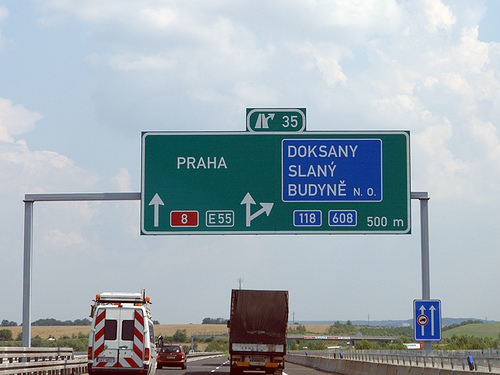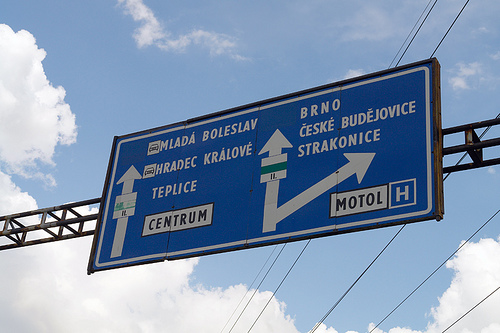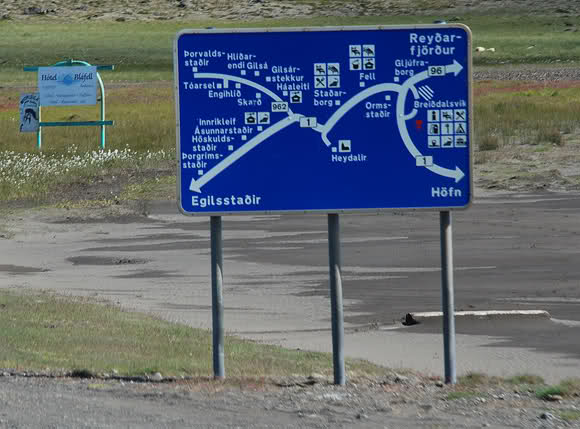
Verkehrsschriften-Wiki-Artikel
Die Slovaken nehmen Futura bold condensed; irgendwie sieht die auf den Schildern leicht deplaciert und semiprofesionell aus, aber so ein kleines Volk darf sich sicher etwas Semiprofessionalität leisten:
Ich frage mich, wie andere Leute (also Ralf) solche Photos machen, da man ja praktisch nie anhalten kann, wo solche Schilder stehen.
Merkwürdig, dass bei der Entfernungsangabe "1000 m" die 1 näher an den anderen Ziffern zu stehen scheint. Man kennt das doch, wenn schon denn schon, eher anders herum, dass die 1, weil schmaler, mehr Raum um sich hat.
Die Slovaken nehmen Futura bold condensed;
Wo ist das Schild her?
Könnte auch ein altes Überbleibsel sein, wie das hier, das ich in Prag fand:
Aktuelle Schilder in Tschechien lehnen sich an das deutsche System an:
Ob die Slowakei wirklich noch die alten Schilder als Standard hat, weiß ich allerdings nicht.
Ich hab mir auf Beifahrerseite ein Stativ mit Fernbedienung montiert. Wobei es mit den heutigen Digitalkameras mit Monitor auf der Rückseite ja auch kein Problem mehr ist, bei der Fahrt ein paar Bilder zu schießen, ohne dass man sein Auge an die Kamera drücken müsste …
Merkwürdig, dass bei der Entfernungsangabe "1000 m" die 1 näher an den anderen Ziffern zu stehen scheint. Man kennt das doch, wenn schon denn schon, eher anders herum, dass die 1, weil schmaler, mehr Raum um sich hat.
Klassischer Fall von Überkompensation, wahrscheinlich. Außerdem werden die sich gedacht haben, daß nur ein verschwindender Teil der potentiellen Rezipienten bei Geschwindigkeiten um die 130 km/h willens ist, einen ordentlichen Ausgleich zu goutieren. Und mit uns haben die einfach nicht gerechnet. :?
Spontan würde ich sagen: Ja. Mir sind jedenfalls etliche Futura-Schilder aufgefallen und ich kann mich nicht an andere erinnern.
Im fortgeschrittenen Stadium sieht das dann so aus.
Falls zufällig jemand in der Nähe ist: Nächte Woche werde ich meine Recherche zum Thema Schrift auf Verkehrsschildern im Rahmen meiner Diplomarbeit erstmals der Öffentlichkeit präsentieren und dabei auch einen Blick auf den aktuellen Stand meiner in Arbeit befindlichen Leitsystem-Schrift gewähren.
woran ich beim lesen die ganze zeit denken musste, was aber nie vorkam: wie beurteilst du die FF Info, die ja meines wissens speziell für schilder/displays/leitsysteme gebaut wurde?
Es gibt ja noch einige weitere Schriften für Beschilderungen. Ich hab sie natürlich alle analysiert und mir eine Meinung gebildet, aber ich will das nicht unbedingt öffentlich auswerten. Es kommt immer auf die Anwendung an und es liegt deshalb in der Verantwortung der Schriftanwender, zu prüfen, ob die eine oder andere Schrift für das anstehende Projekt am besten geeignet ist.
Zwei Fragen, die mir beim Lesen des Artikels kamen, würde ich gerne in die Runde werfen.
Erste Frage bezieht sich auf die Verwendung des doppelstöckigen g. Basiert deine Wahl auf den Versuchen mit deinem Test-Tool? Denn ich stelle mir vor, dass es sicherlich optisch eher »zuschmiert« als das einstöckige. Oder ist hier die prägnantere Form ausschlaggebend gewesen?
Gibt es eine Art Faustregel für die Strichstärkenunterschiede bei positiver und negativer Anwendung? Haben negativ gesetzte Buchstaben beispielsweise 5% schmälere Grundstriche? Oder geht ihr/gehst du dabei ausschließlich nach dem Augenmaß? Gerade bei Logos und Piktogrammen stößt man ja auch häufiger auf dieses Problem.
Ja, unter erschwerten Lesebedingungen war das dreistöckige g deutlich besser erkenn- und unterscheidbar. Ob es zuläuft ist eher eine Frage des Designs. Auch ein zweistöckiges kann zulaufen, wenn die untere Punze zu schmal gehalten ist. Bei meiner Schrift wurde auf genug Luft geachtet. Hat dann nur den Nebeneffekt das der Zeilenabstand größer gewählt werden muss, aber da bei Beschilderungen ja eher die Breite kritisch ist, habe ich diesen kleinen Nachteil zugunsten besserer Erkenn- und Unterscheidbarkeit bewusst in Kauf genommen.
Gute Frage! Ich hab auch nix besseres dazu gefunden und mich per Augenmaß angenähert.
Panno is the retail version of Hangil E-Type, the signing typeface designed for the English names on the bilingual road signs of South Korea. Because the English names can be very long the typeface is narrow. The one weight typeface is available in two styles (positive and negative) and has an extended (Latin) character set. OpenType features include an alternative shape for the figure four and ligatures